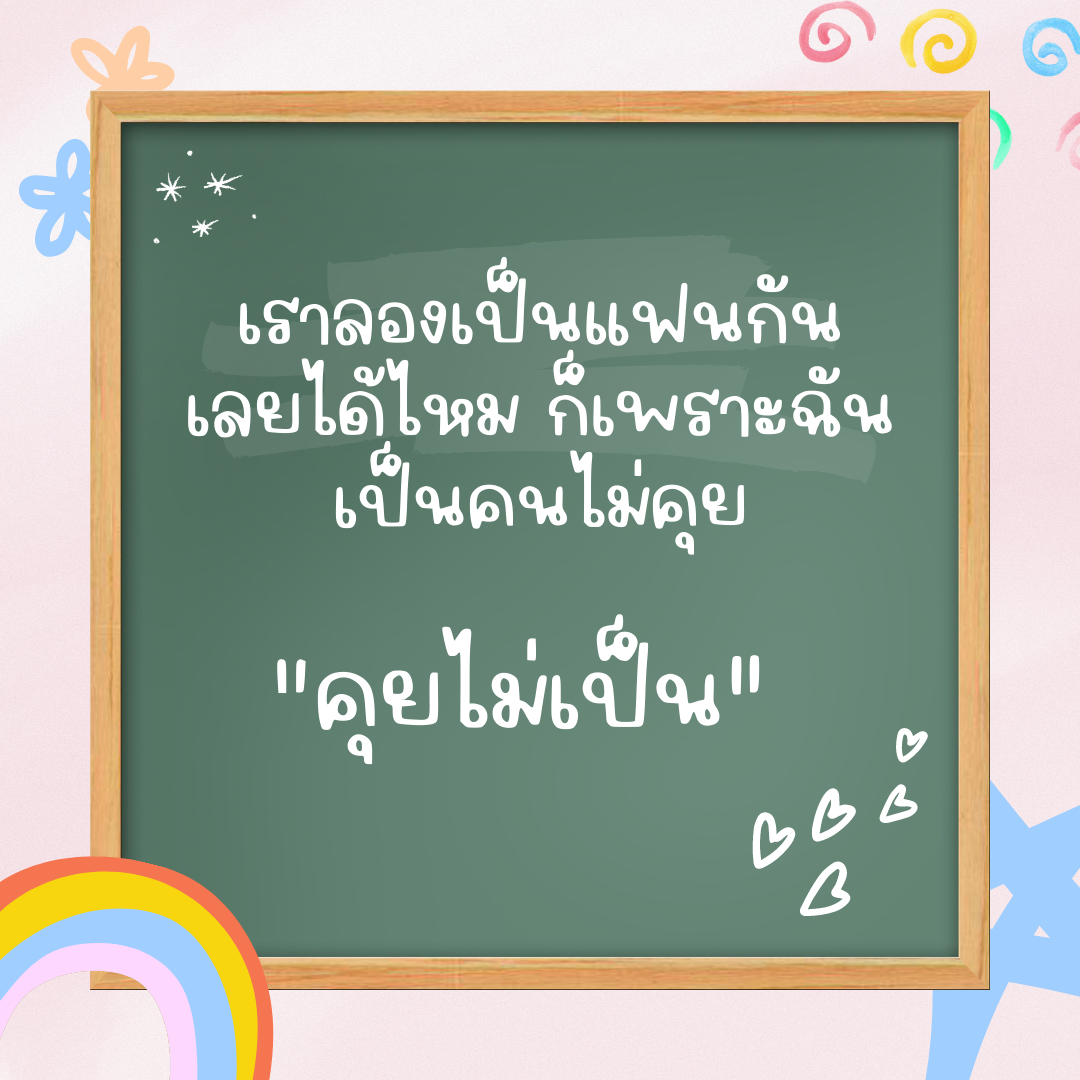
น่ารัก (Naruke)
ฟอนต์ น่ารัก(Naruke) เป็นฟอนต์ลายมือจ๋าๆ ออกไปทางลายมือเด็กเขียนเล่น และมีสไตล์เป็นของตัวเอง แจกฟรีไปเลยเวอร์ชันทดลอง : แบบปกติ 1 น้ำหนัก ใช้ได้เฉพาะแบบส่วนตัว เช่น ใช้ในการศึกษา ใช้จด ใช้ตกแต่งสมุดโน้ตตัวเอง